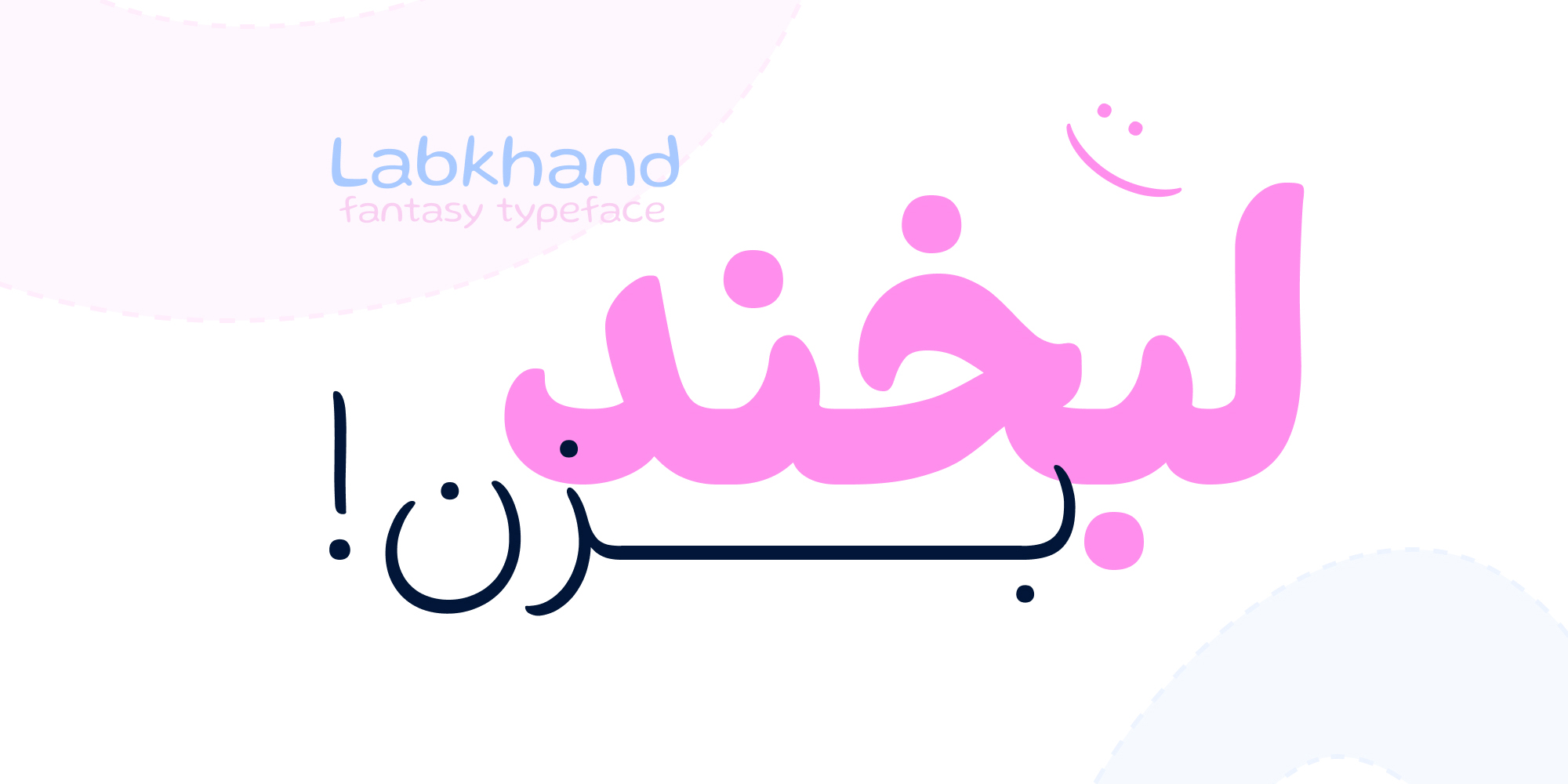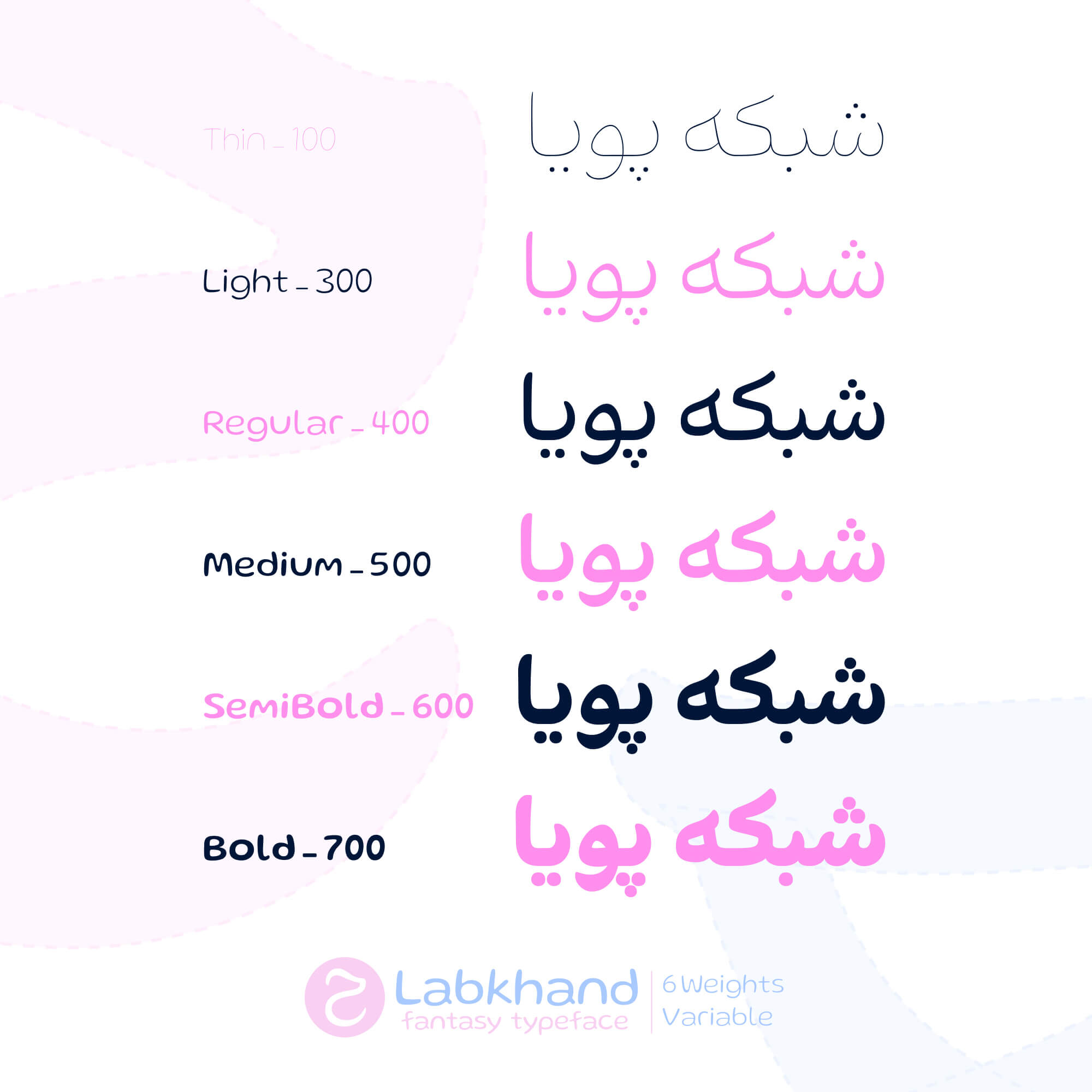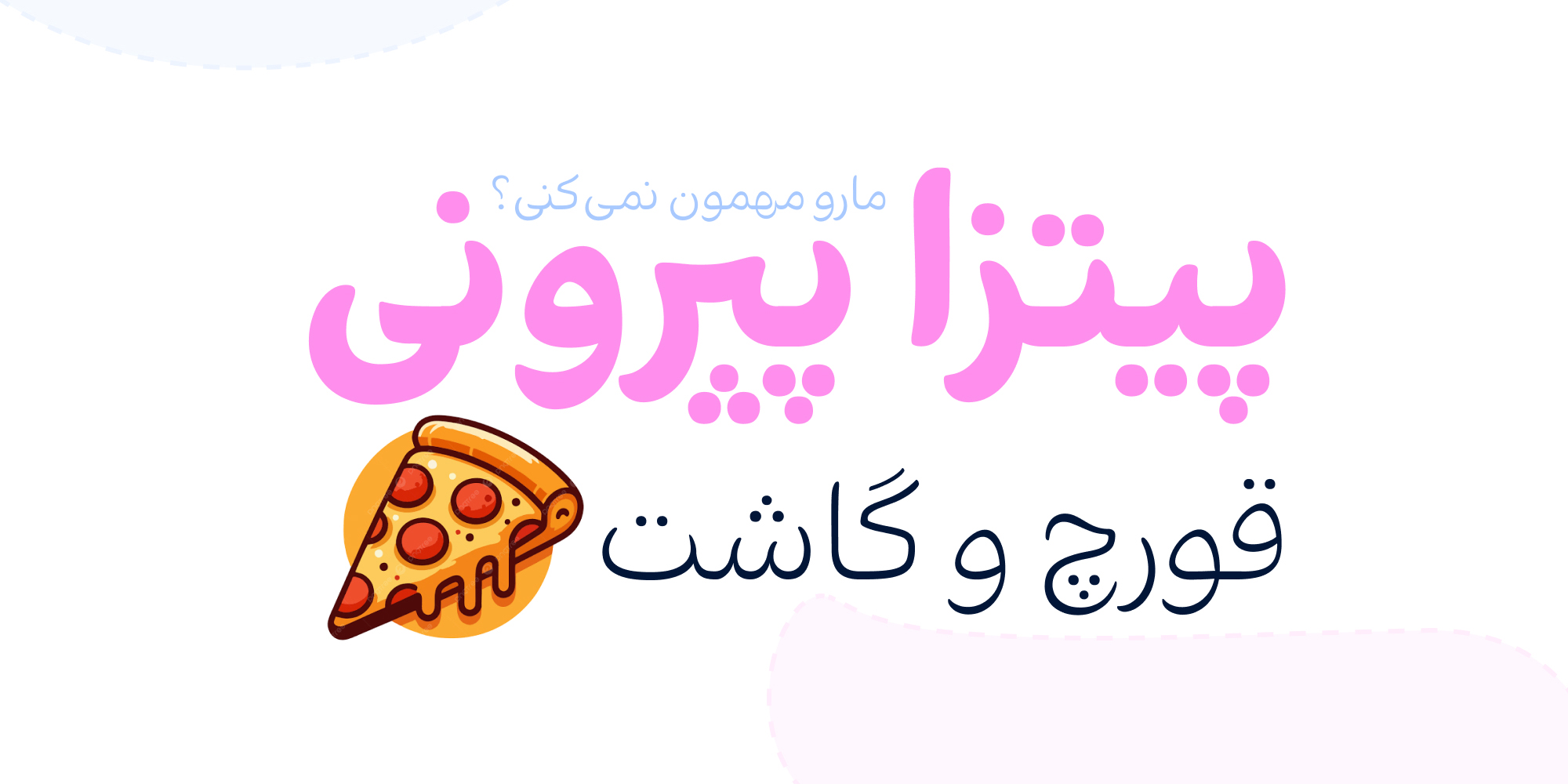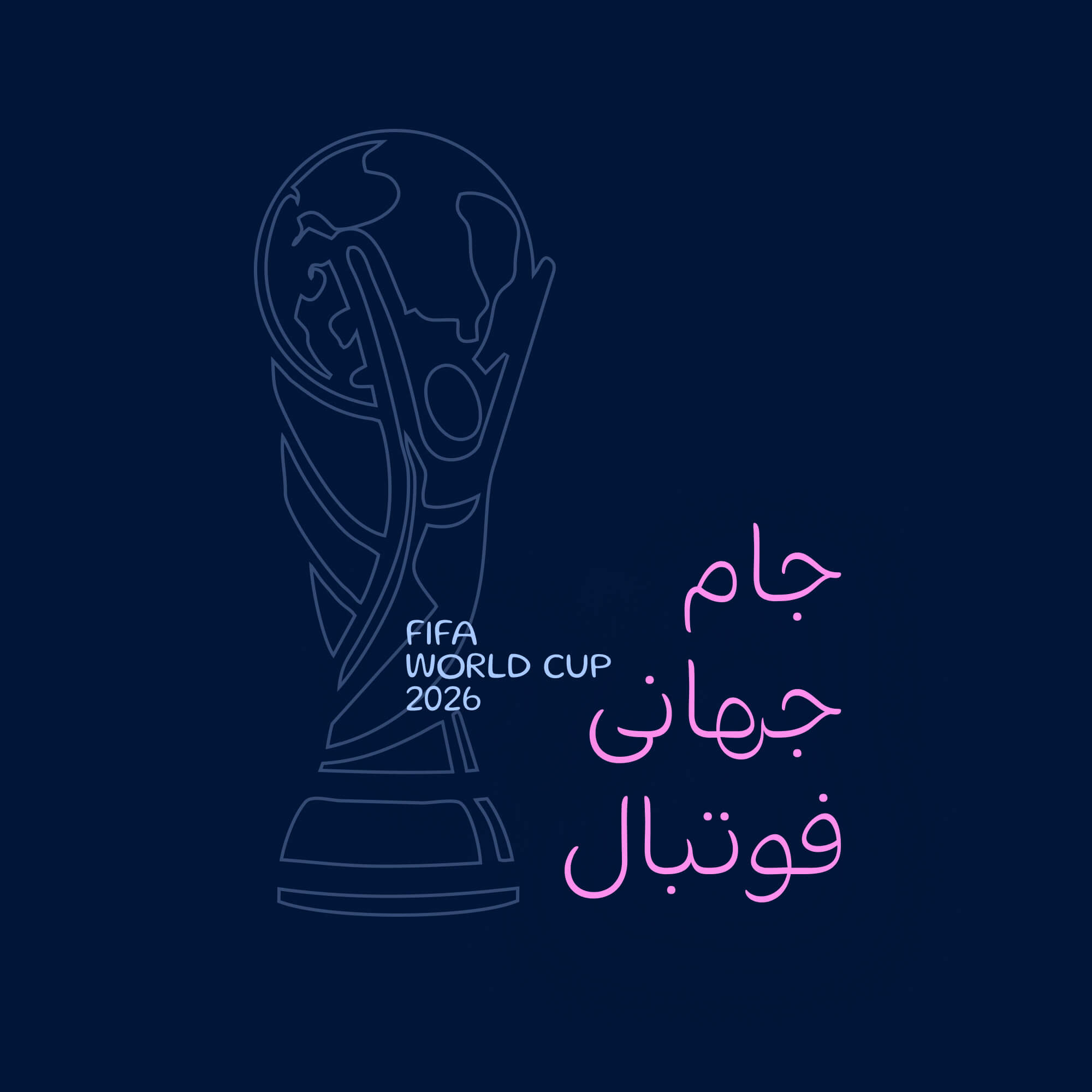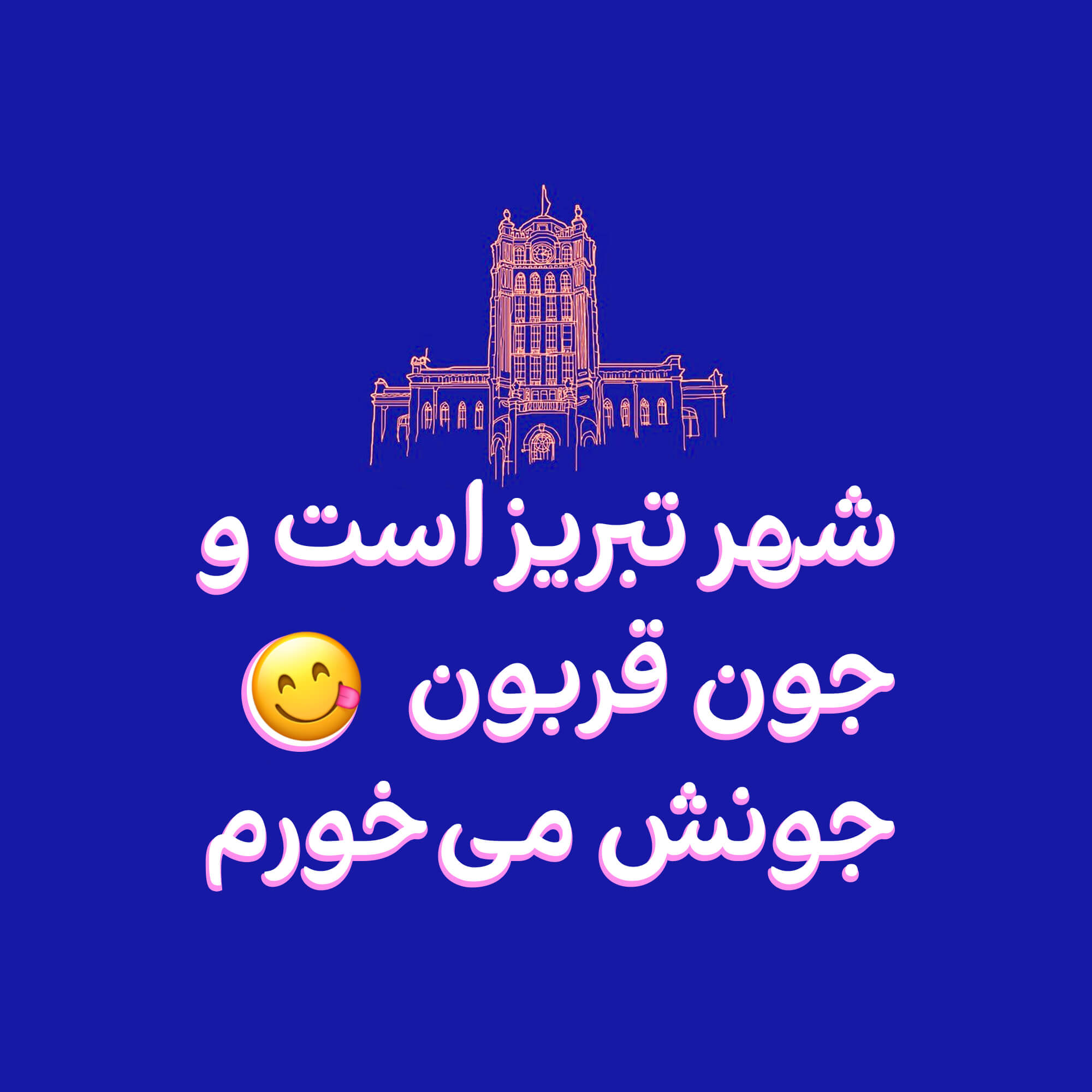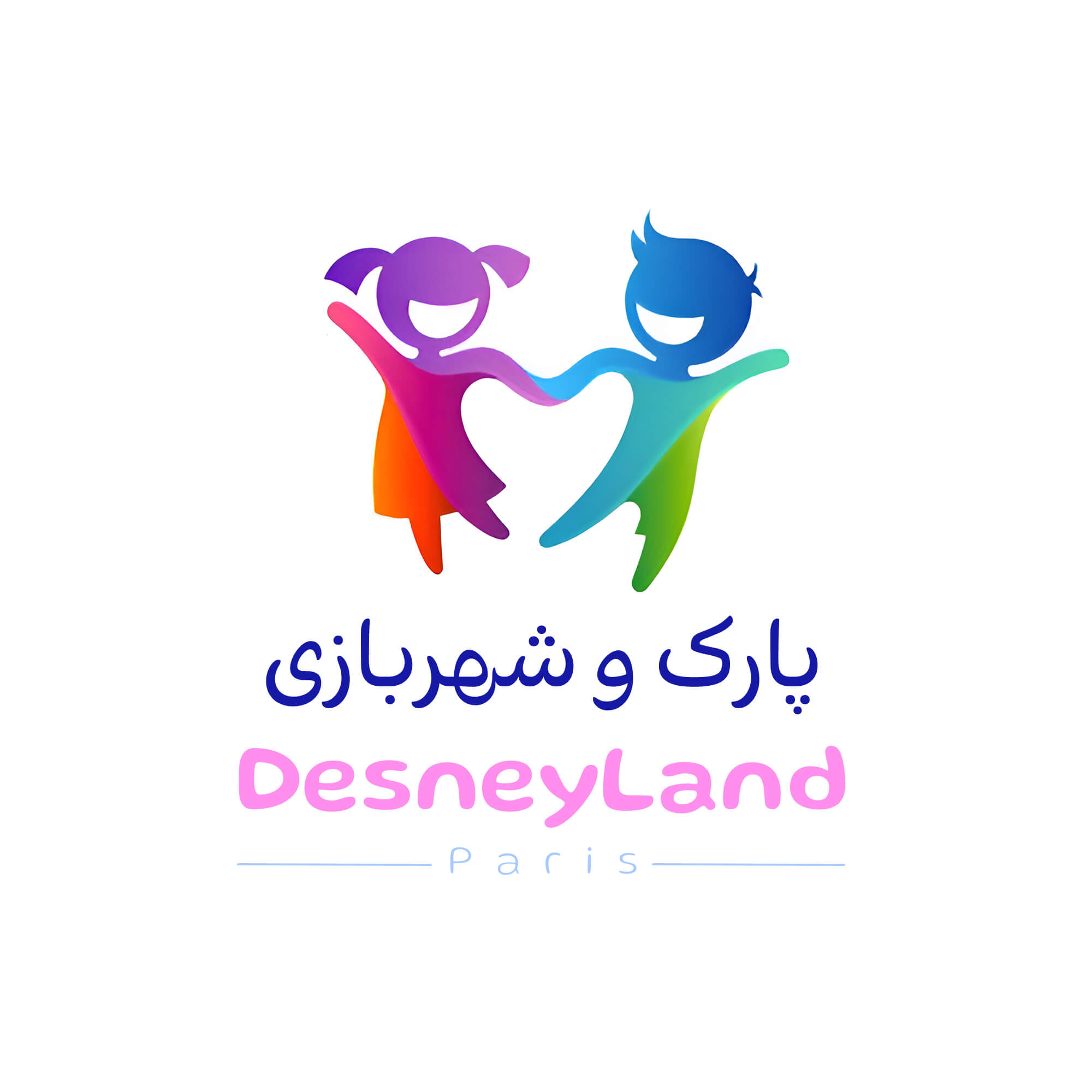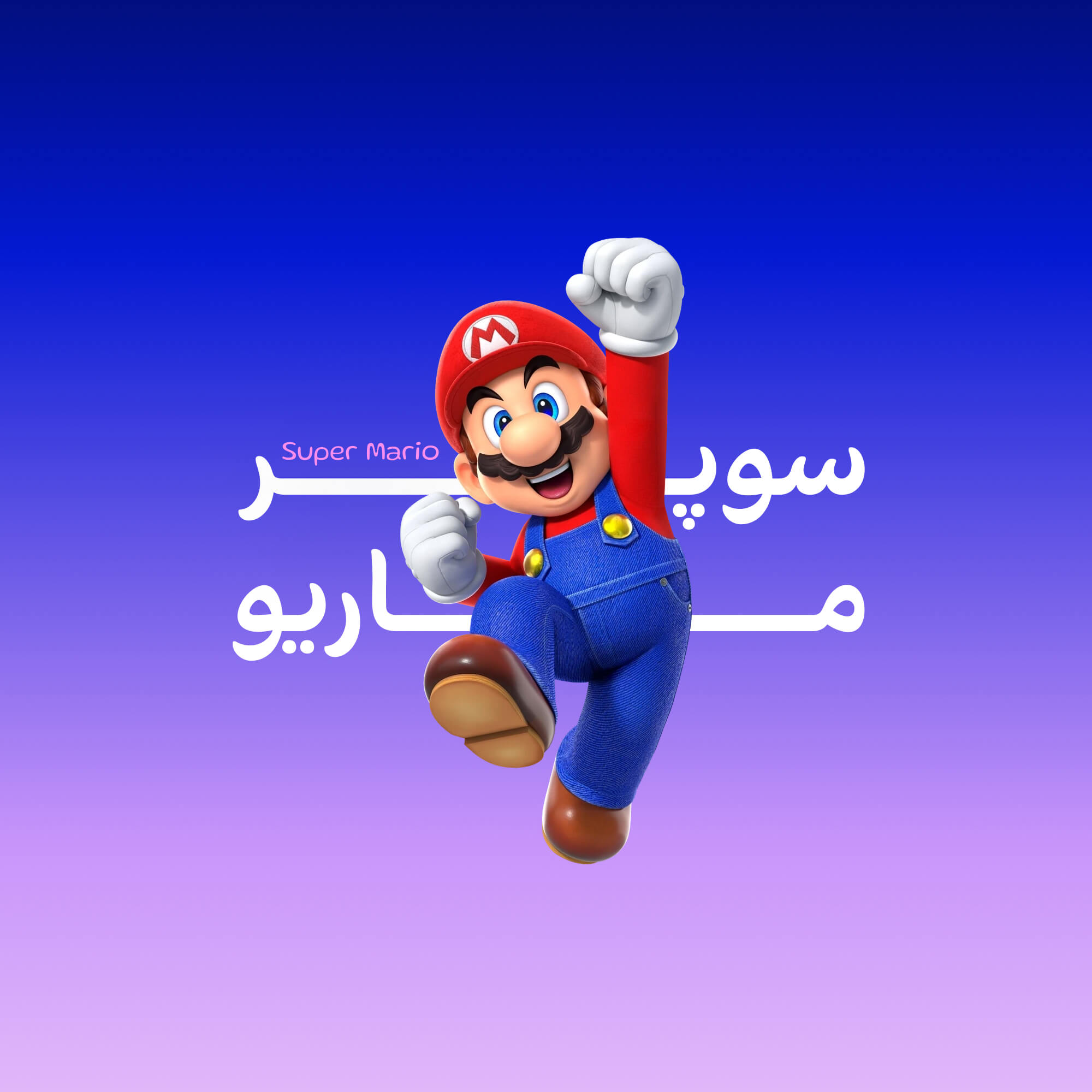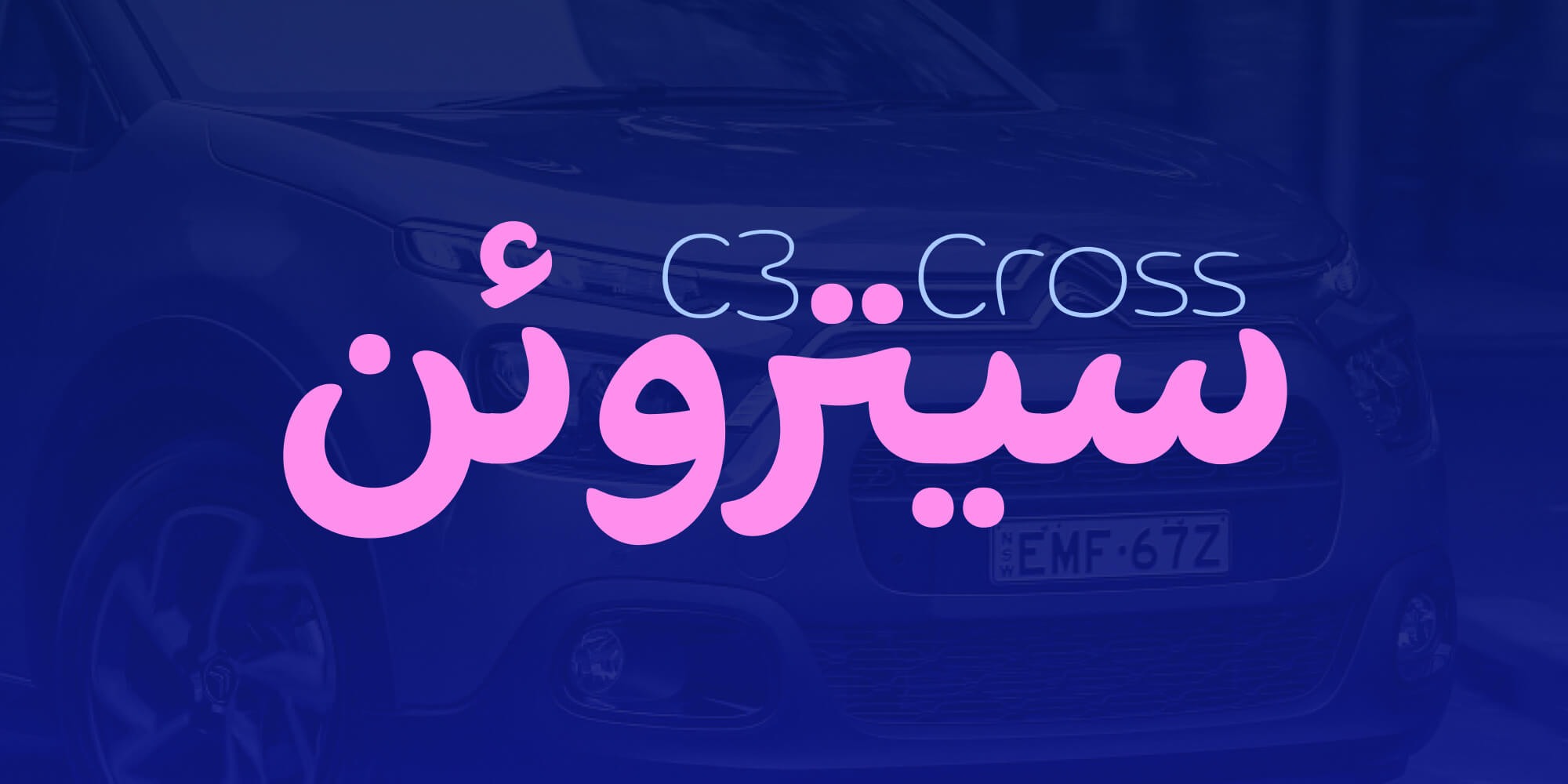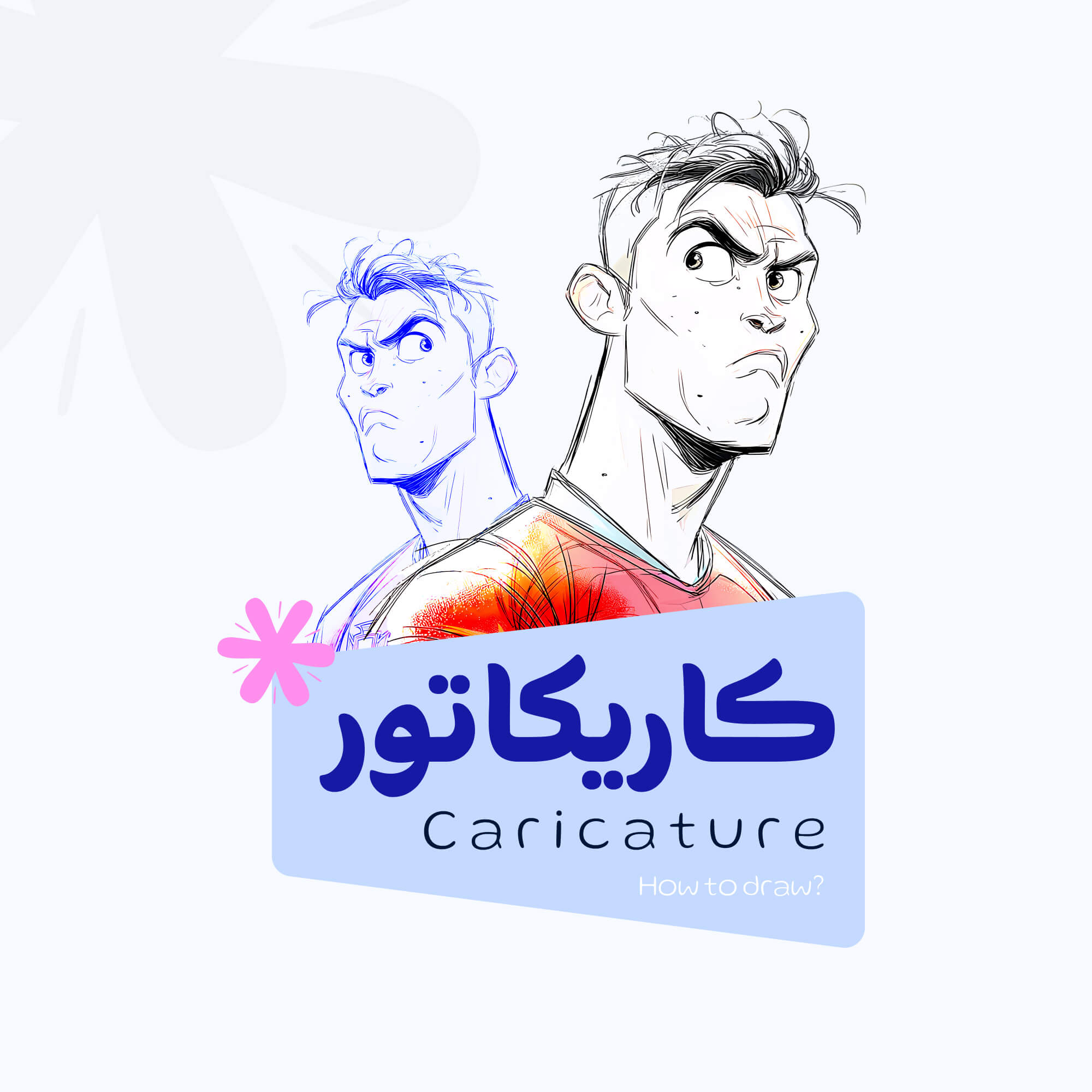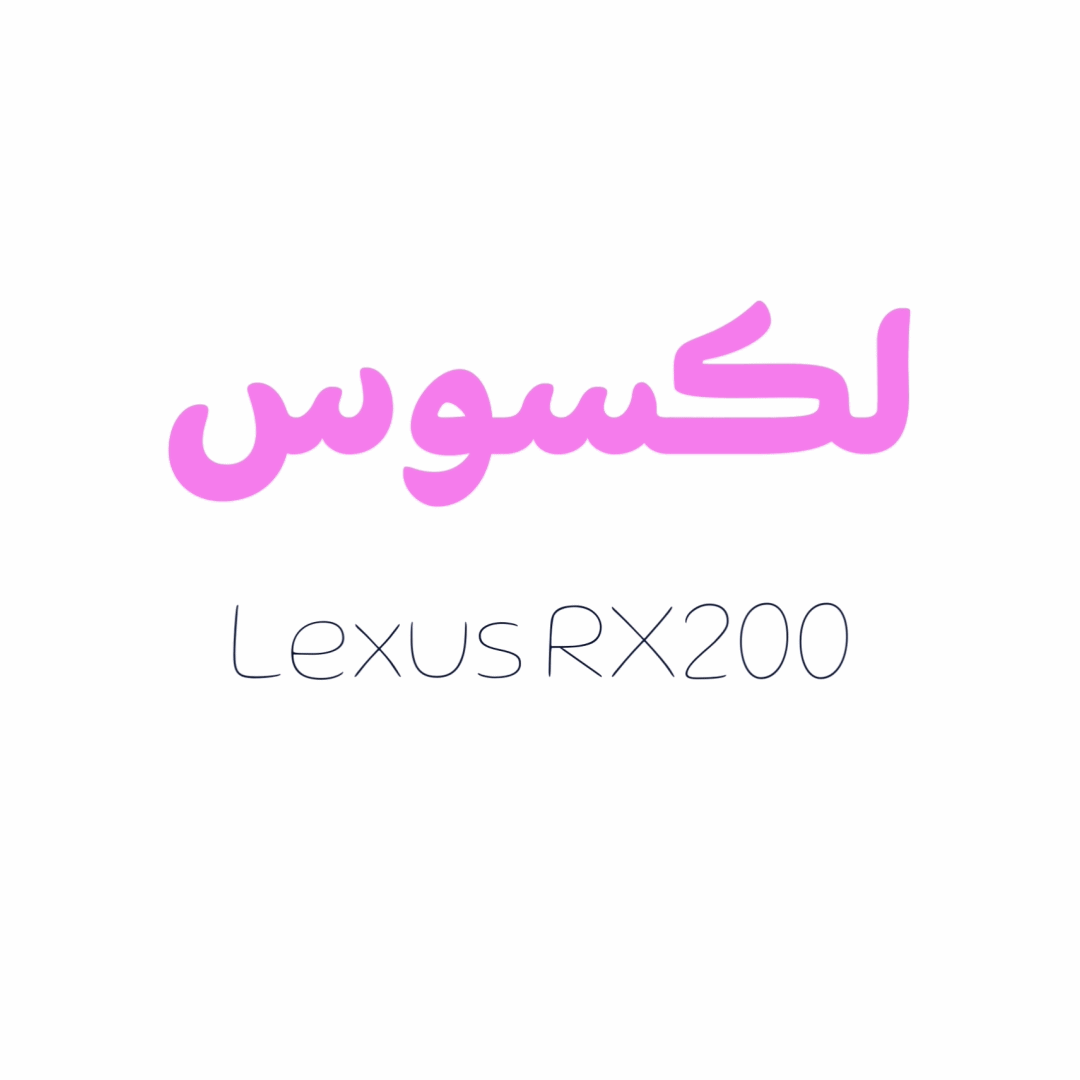
تنوع وزنها و وریبل فونت لبخند (فونت متغیر)
فونت لبخند بر اساس نیازهای طراحان شکل گرفته و خانوادهای شامل ۶ وزن است. این فونت اکثر نیازهای یک طراح را برآورده میکند. وزنهای سنگینتر در بروزرسانیهای بعدی به فونت اضافه خواهد شد.
فونت لبخند در متن و دیسپلی
هندسه، تناسبات و فرم
ترکیبات، جایگزینها و لگیچرها
زبانهای پشتیبانی شده در فونت لبخند
فونت لبخند از زبانهای فارسی، عربی، اردو، کوردی، جاوی و انگلیسی پشتیبانی میکند.
اعداد، ارقام و نمادهای تایپوپول شامل:
. اعداد فارسی، انگلیسی و عربی
. اعداد همعرض
. اعداد پایین رونده (مناسب الاین کردن در کادرها و فضای درج قیمت در دکمه سایتها و بنرهای مربوط به لیست قیمت)
فونت لبخند در کاربرد